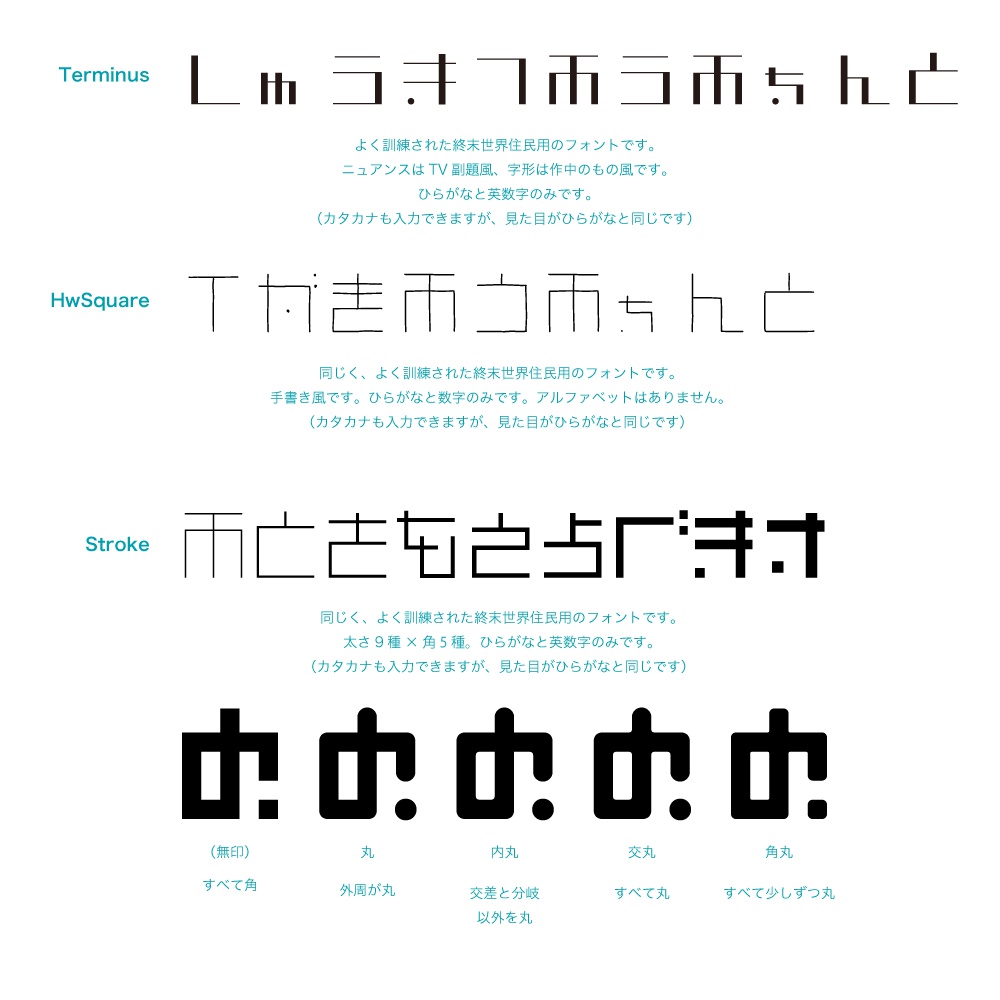
GLT-ごぬんね(アニメ「少女終末旅行」副題風フォント)
(画像は作成中のものです。最新版は2023/07/30夜) TVアニメ「少女終末旅行」に登場する文字をモチーフにしたフォントファイルです。 アニメ・原作とも完結しましたが、まだしばらくバージョンアップしていく予定です。 打てるのは基本的にひらがな・カタカナと英数字だけですが、現在、以下のものは漢字に変換できます。 ・教育漢字(小学校六年生分まで) ・原作単行本6巻(メロンブックス店舗特典含む)までに収録されている副題と「これまでのみちのり」内での場所等 ・サウンドトラックの曲名 ・macOS上での標準の書体見本に使われている文字 また、字形が若干違う書体をいくつか同梱しています。 よろしければご自由にお使いください。 このファイルは二次創作物です。 このファイルの作者は当該の作品の製作関係者とは無関係です。